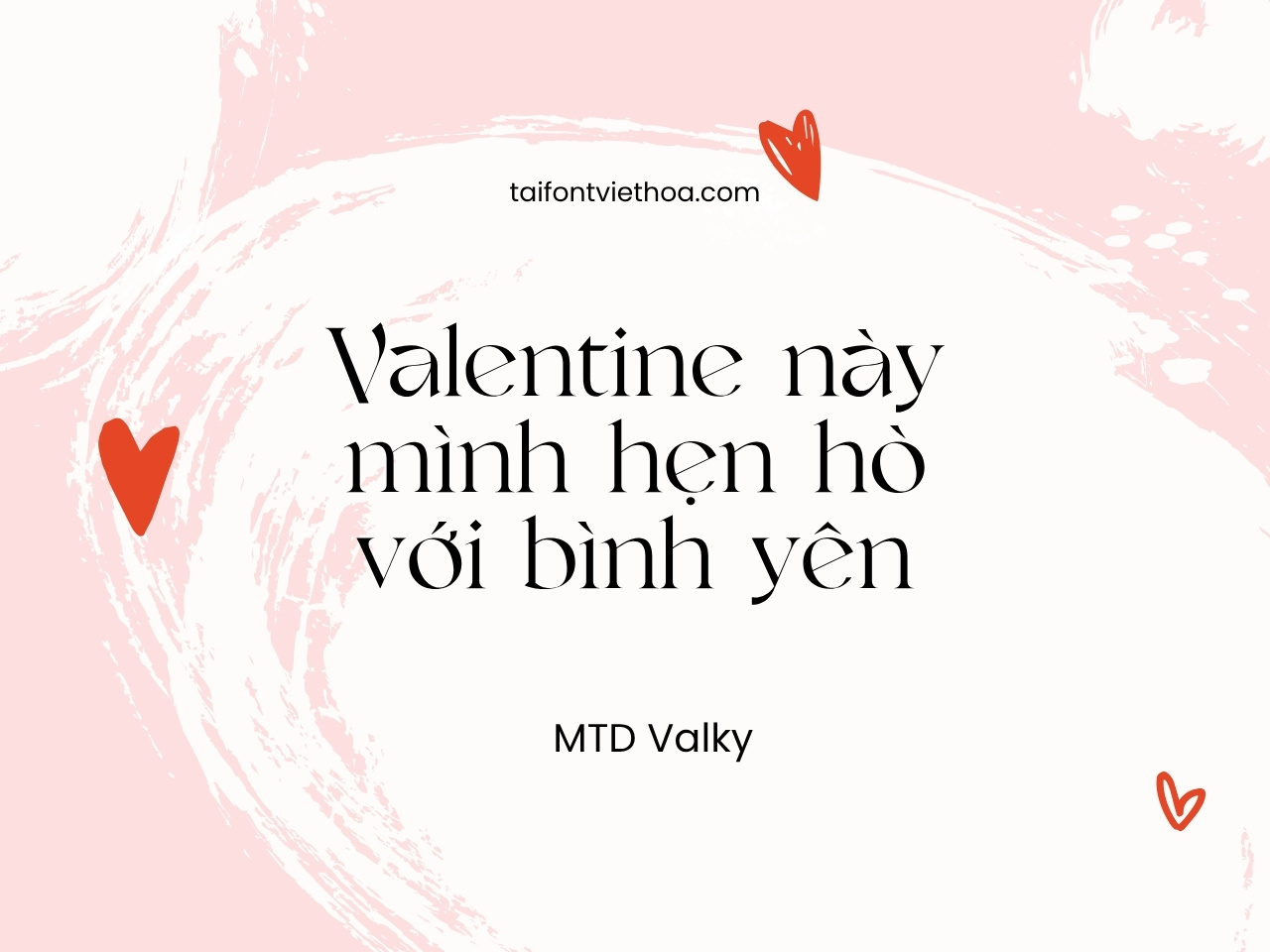
Font việt hóa Valky đầy đủ 4 Font
Giới thiệu về bộ font Valky
Valky là bộ font serif gồm 4 kiểu chữ: Regular, Italic, Bold và Bold Italic – được thiết kế bởi studio MTD Type. Bộ font này mang đậm phong cách editorial cổ điển, kết hợp hài hòa giữa nét sang trọng và nghệ thuật typography hiện đại. Font được phát hành vào khoảng năm 2022 và nhanh chóng trở thành lựa chọn phổ biến trong thiết kế biên tập, thời trang và thương hiệu cao cấp. Bộ font hỗ trợ hơn 70 ngôn ngữ sử dụng hệ chữ Latinh mở rộng, đảm bảo linh hoạt trong các dự án quốc tế.
Phiên bản Việt hóa do nhóm Mộc Hạ thực hiện, đảm bảo hỗ trợ đầy đủ bảng chữ cái tiếng Việt có dấu, đồng thời tinh chỉnh kerning, spacing và cấu trúc unicode để sử dụng mượt mà trên mọi phần mềm thiết kế. Taifontviethoa.com đã sưu tầm và giới thiệu bộ font này như một giải pháp typography chuyên nghiệp, phù hợp với nhu cầu sáng tạo của các nhà thiết kế cần tính linh hoạt và đẳng cấp trong trình bày văn bản, tiêu đề hoặc thương hiệu.
Đặc điểm thiết kế và khả năng ứng dụng
Font Valky có cấu trúc serif cổ điển với phần thân chữ mềm mại, độ dày vừa phải, mang lại cảm giác sang trọng và dễ đọc. Các chữ in hoa được thiết kế mạnh mẽ, nổi bật, trong khi chữ thường lại thanh thoát, giúp tạo nên sự đối lập thú vị về mặt thị giác. Bộ font có hỗ trợ italic và bold, rất phù hợp cho hệ thống phân cấp nội dung. Các glyphs mở rộng đi kèm giúp tăng khả năng trình bày linh hoạt, nhất là trong các dự án editorial hoặc hệ thống nhận diện thương hiệu cao cấp.
Bộ font Valky đặc biệt phù hợp với các lĩnh vực như thiết kế tạp chí, biên tập nội dung, logo thương hiệu sang trọng, thiệp cưới, thời trang, làm đẹp và bao bì sản phẩm nghệ thuật. Ngoài ra, font còn ứng dụng tốt trong các ngành như giáo dục, công nghệ, bất động sản và quảng cáo mùa lễ hội như Tết, Valentine, hoặc sự kiện truyền thống.